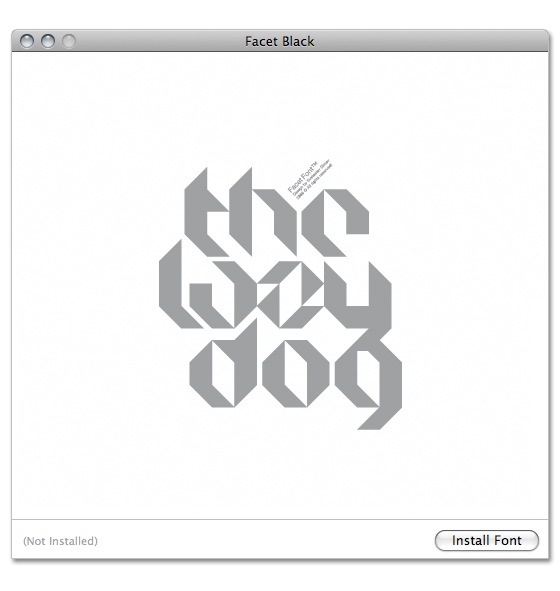
free Font Facet
free Font Facet – Facet ist eine freie Schriftart die man wunderbar für Verzierungen und Headlines einsetzen kann. Die Lesbarkeit ist zwar eher schlecht aber dafür macht der freeFont durch seine Struktur und schlanke Anmutung was her. Gerade wenns über die Wortbedeutung hinausgehen soll, ist mit Facet ein ausdrucksvoller Font am Start!